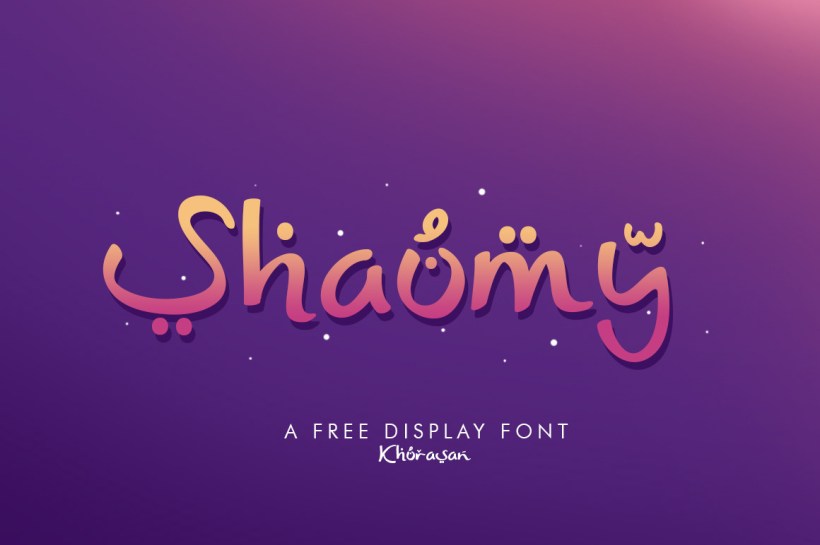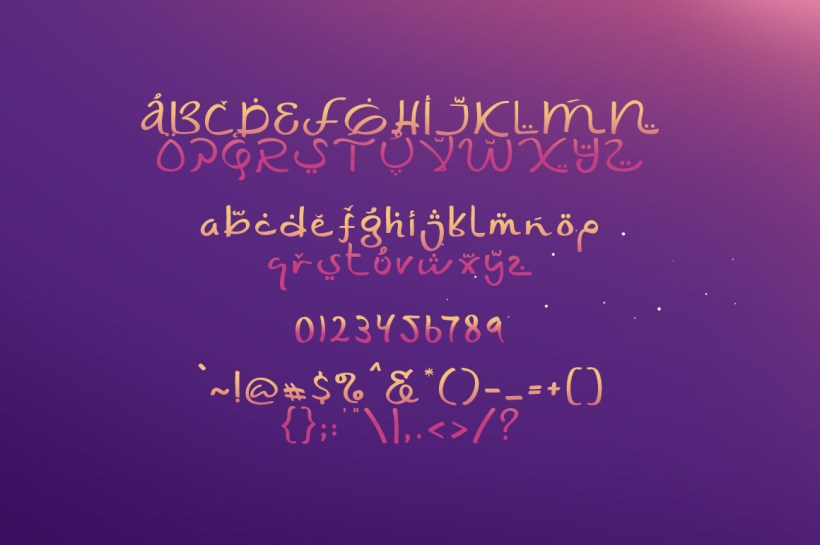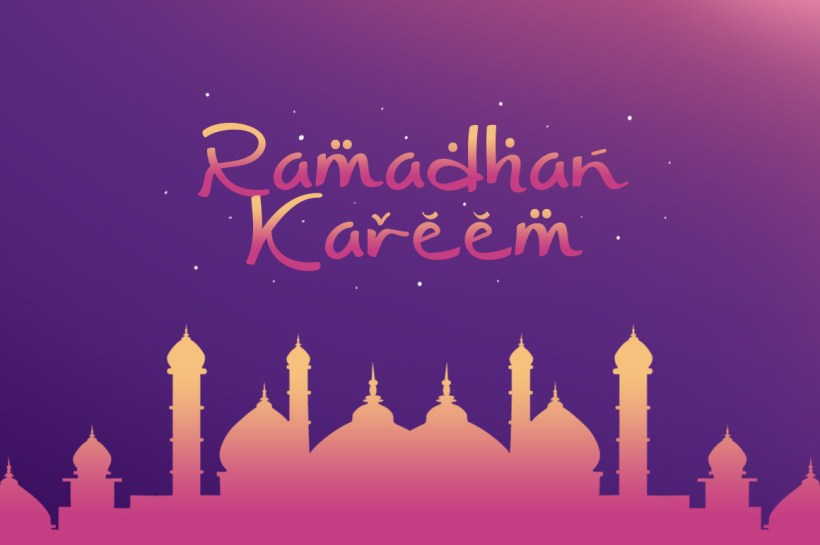
En ce premier jour de Ramadan, je vous propose une police d’écriture dont les lettres rappelle fortement la calligraphie arabe. Créée par Syaf Rizal, elle peut être très utile pour la conception de toutes sortes de graphismes ou tout simplement pour souhaiter un bon Ramadan à nos amis musulmans !